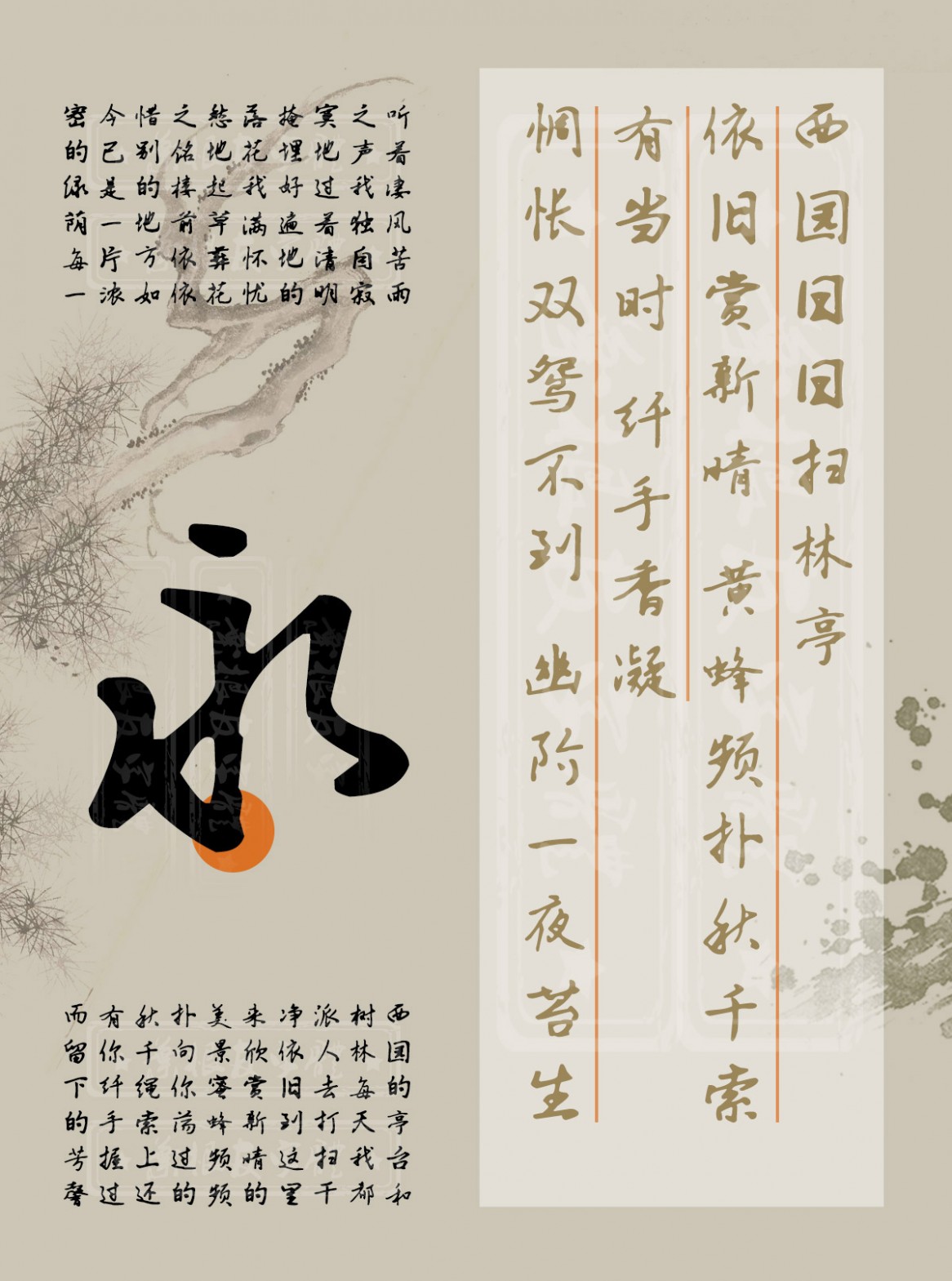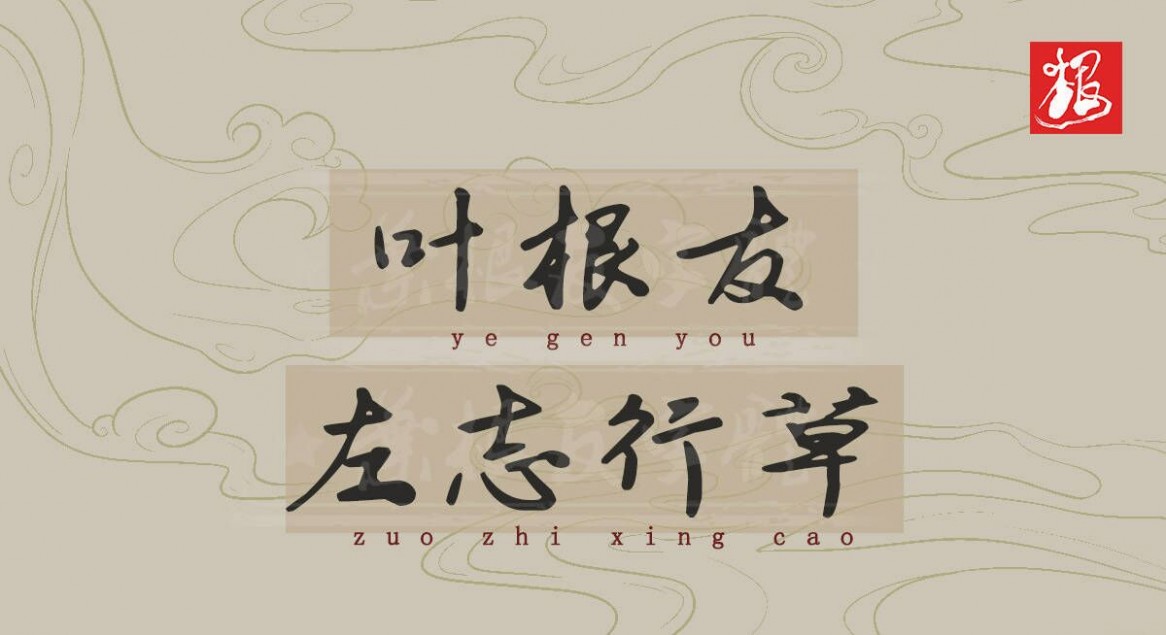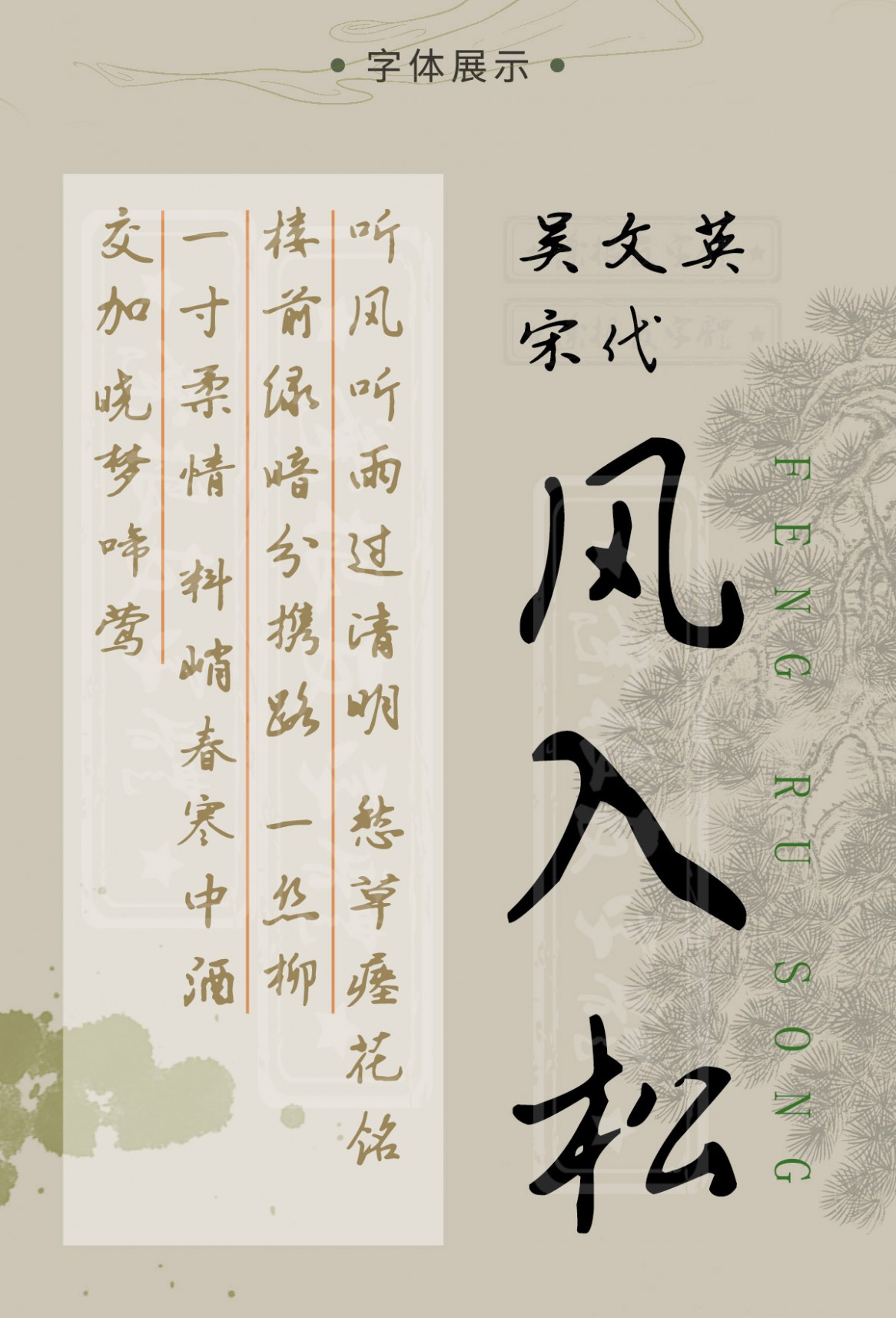
葉根友左志行草
字體介紹
葉根友左志行草是葉根友系列字體中的一款藝術(shù)手寫字體,字體筆觸勻稱,書寫靈動,有著很好的視覺感,適合應(yīng)用于藝術(shù)設(shè)計(jì)、平面宣傳設(shè)計(jì)、網(wǎng)頁設(shè)計(jì),書法字帖等領(lǐng)域,需要的朋友可以前來字體家官網(wǎng)下載。